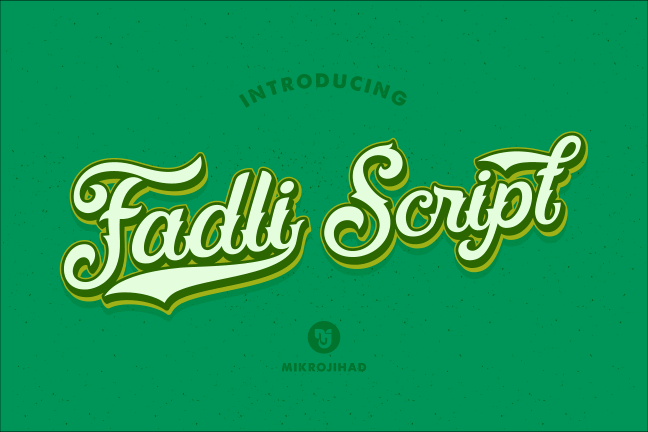
Fadli Script font – Download Grátis
A Fadli Script é uma elegante escolha para designers que buscam a essência das fontes Blackletter, oferecendo estilo com profundidade e elegância. Hamilton, o designer desta curiosa fonte, criou algo que parece ter saído de um antigo documento arquivado, trazendo à vida elementos de gótico medieval num formato moderno. Se você está em busca de uma fonte que vai além do óbvio, a Fadli Script é certamente o caminho para explorar. Com linhas finas e traços complexos, esta fonte Blackletter proporciona um toque autêntico e sofisticado aos seus projetos, seja eletrônico ou impresso. Sua capacidade de criar texturas distintivas faz dela uma opção versátil para qualquer aplicação visual que valorize a história e o estilo do gótico tardio.